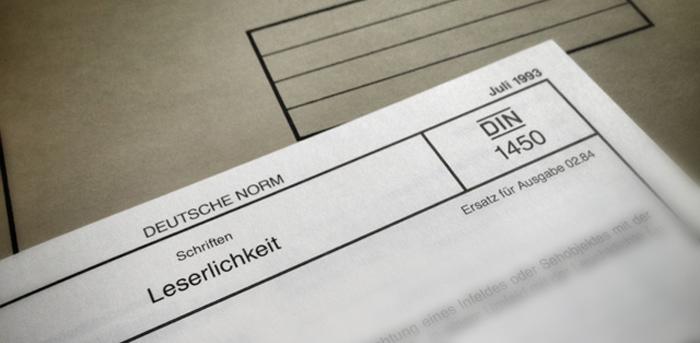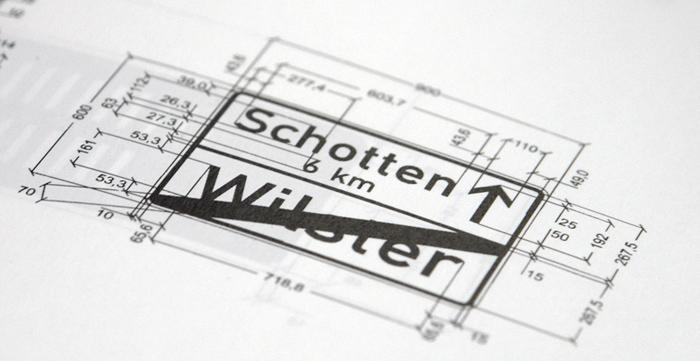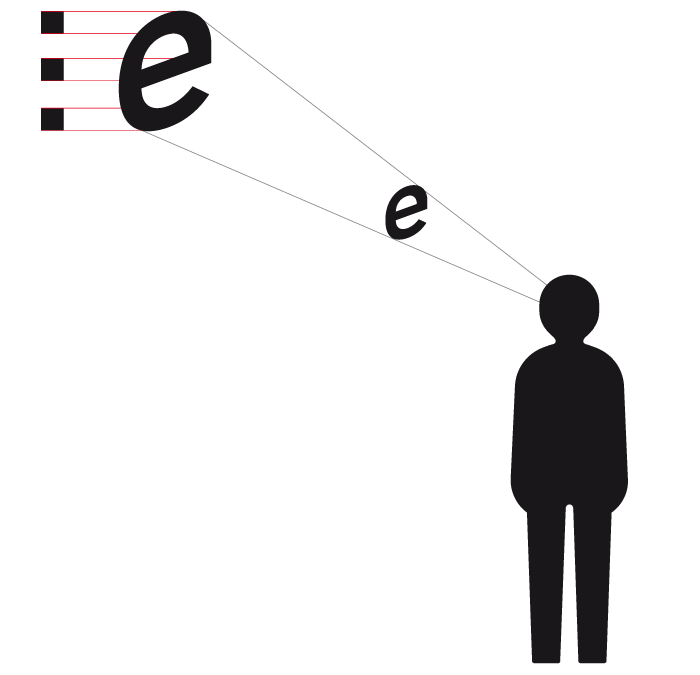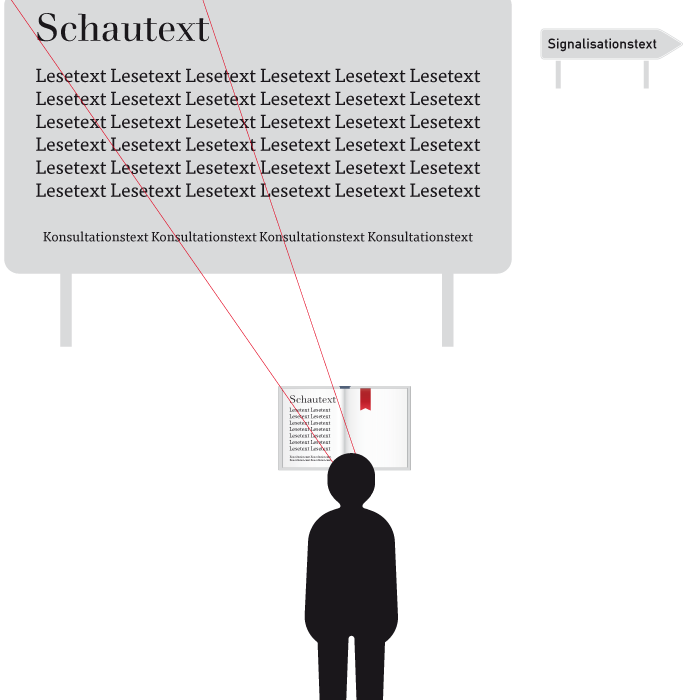
DIN 1450 – warum eine Norm zur Leserlichkeit von Schrift sinnvoll ist
Vor kurzem wurde die umfassend erweitere Norm DIN 1450 Leserlichkeit veröffentlich. Diese Meldung stößt bei professionellen Schriftnutzern nicht automatisch auf Begeisterung. Es macht sich eher eine gewisse Skepsis breit, begleitet von der Frage, wozu diese Norm nötig sein solle. Schließlich ging es doch bisher auch ohne.
Die skeptische Haltung mag sich auch schon auf das System der DIN-Normen an sich beziehen. Viele denken beim Deutschen Institut für Normung an eine verstaubte Behörde, in der Staatsbedienstete den lieben langen Tag irgendwelche Dinge normieren. Und dies fernab von der Praxis und daher vermutet man in den Normen nicht selten nur lauter unnötige oder gegebenenfalls sogar unsinnige Einschränkungen für die Menschen.
Tatsächlich ist das DIN ein eingetragener Verein, der externen Unternehmen und Organisationen aus Handel, Industrie, Wissenschaft etc. bei der Erstellung von Normen behilflich ist. Erstellt werden die Normen dabei von Ausschüssen, die sich aus externen Fachleuten des jeweiligen Gebietes zusammensetzen.
Und letztendlich profitieren wir alle von dieser Normarbeit. Sie sorgt für Qualitätssicherung, Gebrauchsfähigkeit und niedrige Preise durch herstellerübergreifende Kompatibilität. Und nicht selten machen die Normen unser Leben einfacher und sicherer, da sie Qualitäts- und Sicherheitsstandards für alle Dinge setzen, mit denen wir im Alltag in Berührung kommen. Von der automatischen Drehtür bis zum Hochwasserschutzdamm – kaum ein Objekt ist nicht von Normen tangiert. Und Schrift macht dabei keine Ausnahme, denn auch sie kann entsprechende Sicherheitsrelevanz besitzen.
Die Hintergründe
Besonders hohe Anforderungen an die Leserlichkeit von Schrift haben Menschen mit eingeschränktem Sehvermögen. Daher überrascht es auch nicht, dass die Überarbeitung der DIN 1450 auf Initiate dieser Nutzergruppe erfolgte. Der Deutsche Blinden- und Sehbehindertenverband e.V. (DBSV) sah als Interessenvertreter die besonderen Anforderungen dieser Nutzergruppe in der Praxis oft nur unzureichend berücksichtigt und regte daher eine Verbesserung der Norm an.
Denn letztere hatte in der bisherigen Fassung (DIN 1450:1993-07) nur ein recht beschränktes Einsatzgebiet. Im direkten Zusammenspiel mit der allseits bekannten DIN 1451 gab sie Empfehlungen für Beschilderungen im öffentlichen Raum. Sie war jedoch schwerlich auf die Vielfalt heutiger Schriften und Schriftanwendungen übertragbar.
Mit der Überarbeitung wurde daher das Ziel verfolgt, alle verkehrsüblichen Schriftanwendungen abzudecken und dafür sinnvolle und allgemeine Empfehlungen zu geben.
Beschilderungen im öffentlichen Raum. Ein typisches Einsatzgebiet für das Duo DIN 1450 und DIN 1451
Von Fakten und Bauchentscheidungen
Beim Einsatz von Schriften kommen unzählige Einflussfaktoren zum Tragen, die die Leserlichkeit beeinflussen. Man denke an die unterschiedlichen Bedruckstoffe und Darstellungsmedien, die unzähligen typografischen Satzparameter (Schriftwahl, Laufweite, Zeilenabstand, Kontraste etc.) und die persönlichen Vorraussetzungen (Alter, Sehstärke etc.) beim Leser. Die aktuelle Norm nennt ganze 44 solcher Einflussfaktoren.
Um diese verschiedensten Einflüsse sinnvoll abzuwägen und zu möglichst leserlichem Textsatz zu kommen, benutzt ein Grafikdesigner das Wissen aus seiner Ausbildung und seine Berufserfahrung. Die Ausübung dieses Wissens und dieser Erfahrung nennt man im Englischen recht treffend »educated guessing«, also wörtlich etwa »fundiertes Raten«. Der Grafikdesigner kann seine unzähligen gestalterischen Detail-Entscheidungen nicht einzeln wissenschaftlich untermauern, sie sind aber natürlich auch nicht willkürlich, sondern basieren auf entsprechender Erfahrung des Designers bzw. des ganzen Berufsstandes.
Doch »fundiertes Raten« hat auch seine Grenzen. Kann ein Designer wirklich immer korrekt »erraten«, in welcher Größe die Lösch-Einrichtungen und Fluchtpläne in einem Flughafen oder einer U-Bahn-Station beschriften werden müssen, damit sie aus einer bestimmten Entfernung lesbar sind? Kann er immer und zweifellos die gegebenenfalls über Leben und Tod entscheidenden Texte auf Medizin-Verpackungen und Beipackzetteln leserlich setzen und dabei auch die besonderen Bedürfnisse älterer und sehbehinderter Menschen berücksichtigen? Möchte er für die in diesen Fragen gefällten »Bauchentscheidungen« auch die Verantwortung übernehmen, wenn es Nachhinein zu Problemen kommt? Und wie soll der Anspruch der Leser nach guter Leserlichkeit z.B. gegen die Interessen von Bauherren eines Gebäudes oder den Pharma-Herstellern durchgesetzt werden, die vielleicht kein großes Interesse daran haben, die sicherheitsrelevanten Informationen möglichst groß und unmissverständlich zu präsentieren?
Dann reicht es einfach nicht mehr aus, nur auf die Erfahrung eines Grafikdesigners zu verweisen. Wie in anderen Bereichen auch, schaffen klare Standards Planungssicherheit für alle Seiten. Und davon profitieren natürlich auch die Grafikdesigner. Sie müssen sich nicht mehr allein auf ihre Bauchentscheidungen verlassen, sondern haben mit der DIN 1450 ein praktikables Werkzeug an der Hand, dem sie nicht folgen müssen, aber mit dem sie ihre Entscheidungen bei Bedarf abgleichen können. So wie man mikrotypografische Satzkonventionen vielleicht gern in Detailtypgrafie nachschlägt, so kann man nun auch fundierte Leserlichkeitsparameter in der DIN 1450 nachschlagen und sich in der Anwendung auf sie berufen. Eine Option, von der die gesamte Branche und natürlich die Leser der gesetzten Texte profitieren können.
Die Normen bilden übrigens lediglich eine verlässliche Grundlage, auf die sich alle beziehen können. Grafikdesigner sind also nicht gezwungen, Ihre Gestaltung nach den Vorgaben der DIN-Norm anzufertigen. Möglich ist jedoch, dass zukünftige Gesetzesvorlagen für konkrete Anwendungsbereiche die Einhaltung der Norm vorschreiben. So könnte zum Beispiel theoretisch ein Gesetz zur Lebensmittelkennzeichnung explizit die Einhaltung der DIN 1450 für diese spezifische Anwendung fordern.
Doch wo immer zukünftig für den Leser besonders relevante Informationen (z.B. in Bezug auf Gesundheit, Sicherheit, Orientierung etc.) präsentiert werden und durch möglichst optimale Leserlichkeit ein barrierefreier Zugang für eine breite Nutzerschicht garantiert werden soll, kann die Norm eine verlässliche Grundlage zur Ermittlung der idealen Satzparameter darstellen und damit gute Dienste erweisen – für Gestalter und Leser der Texte gleichermaßen.